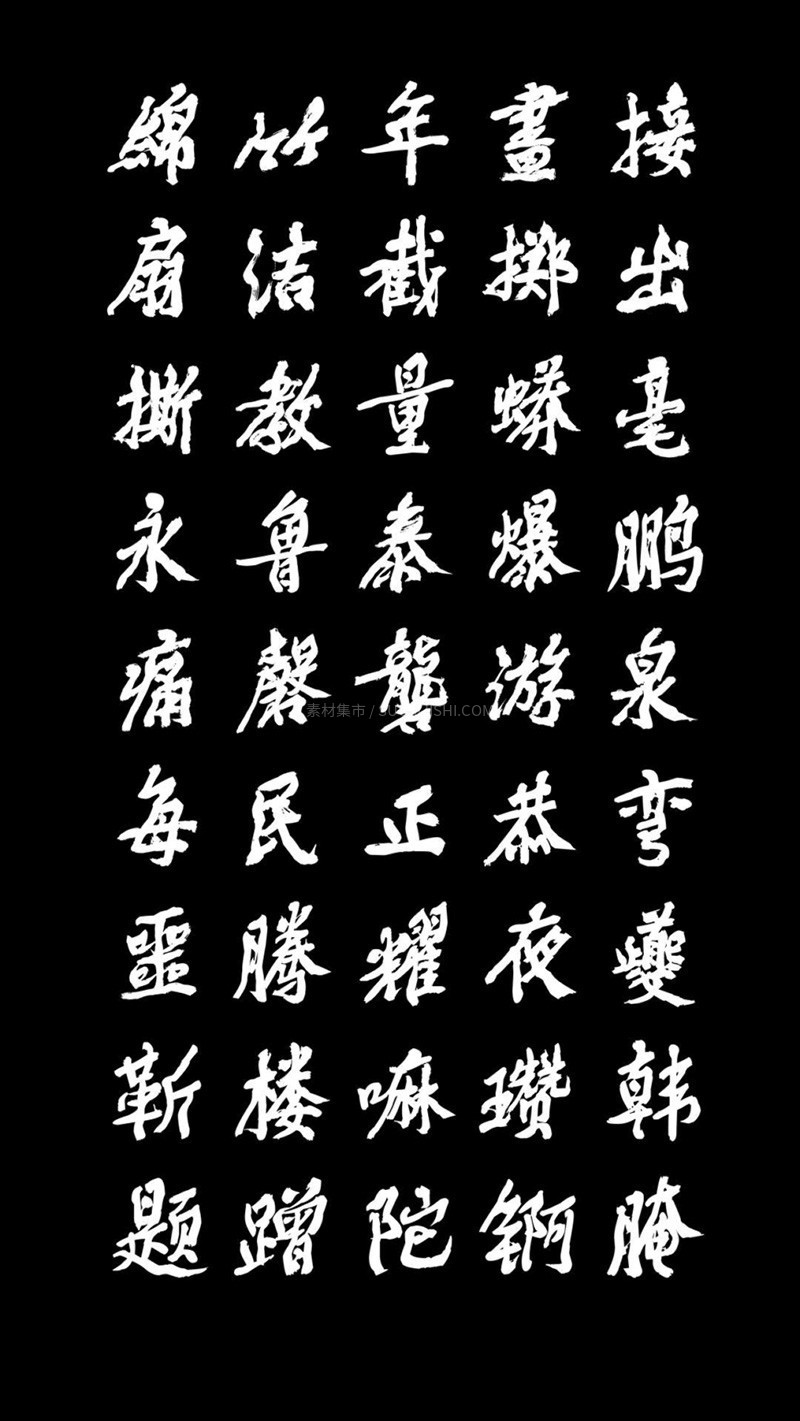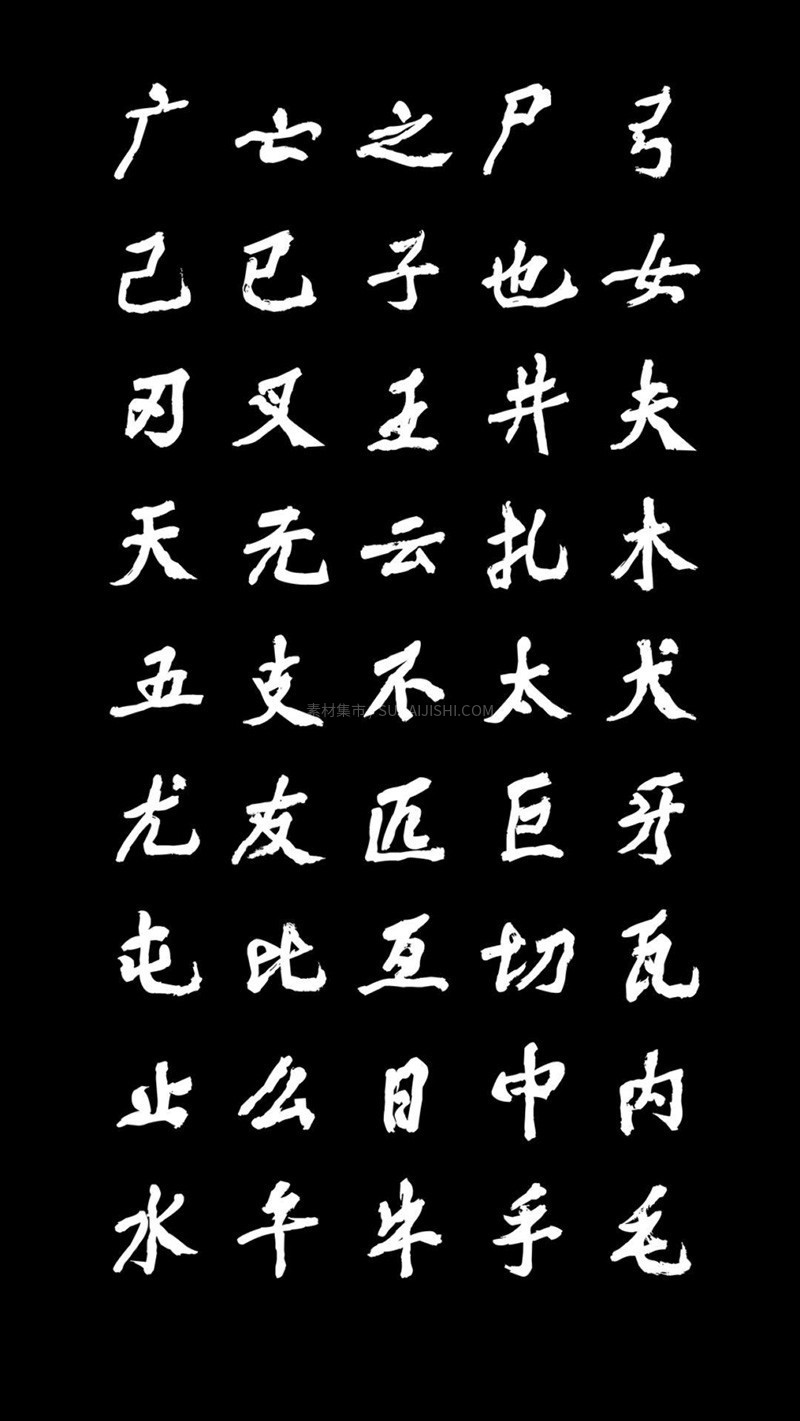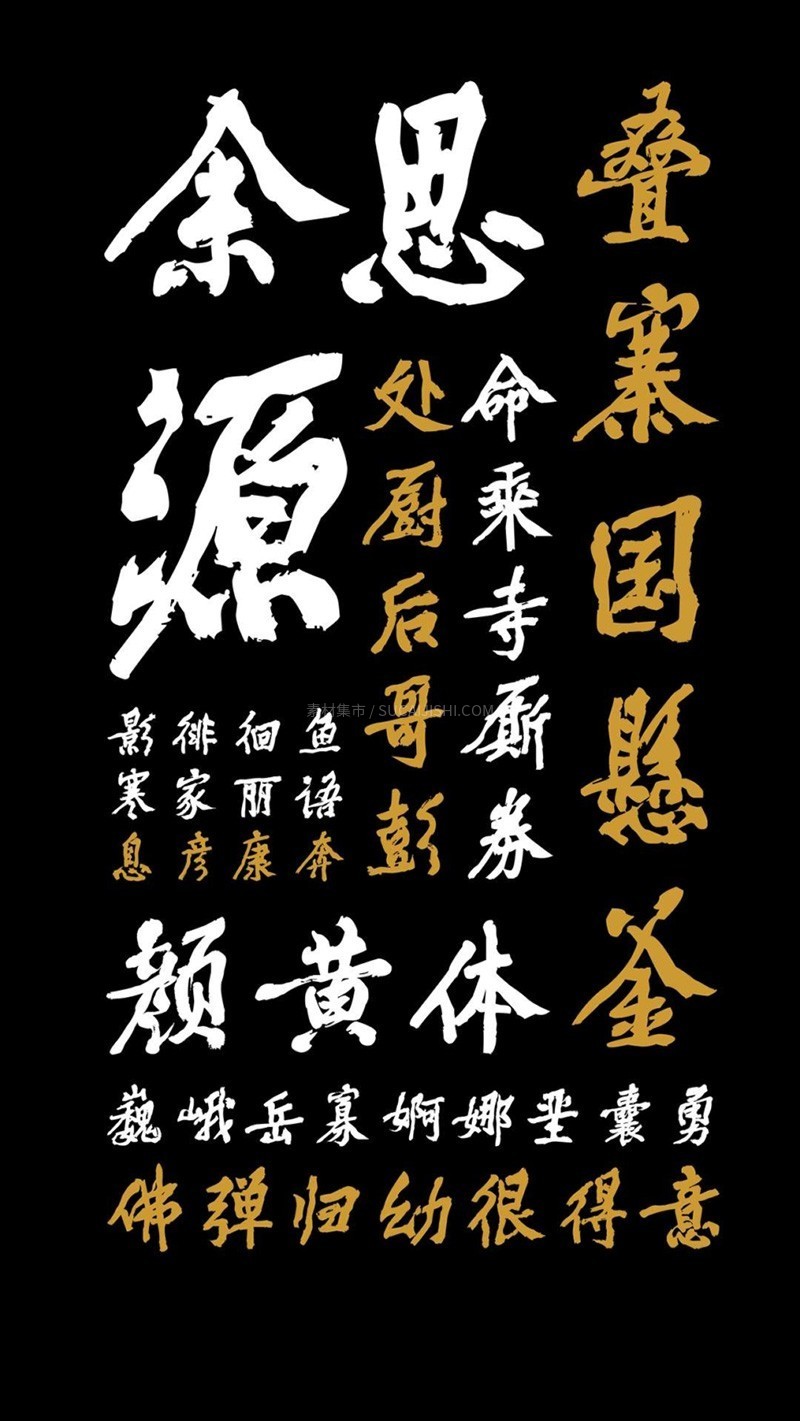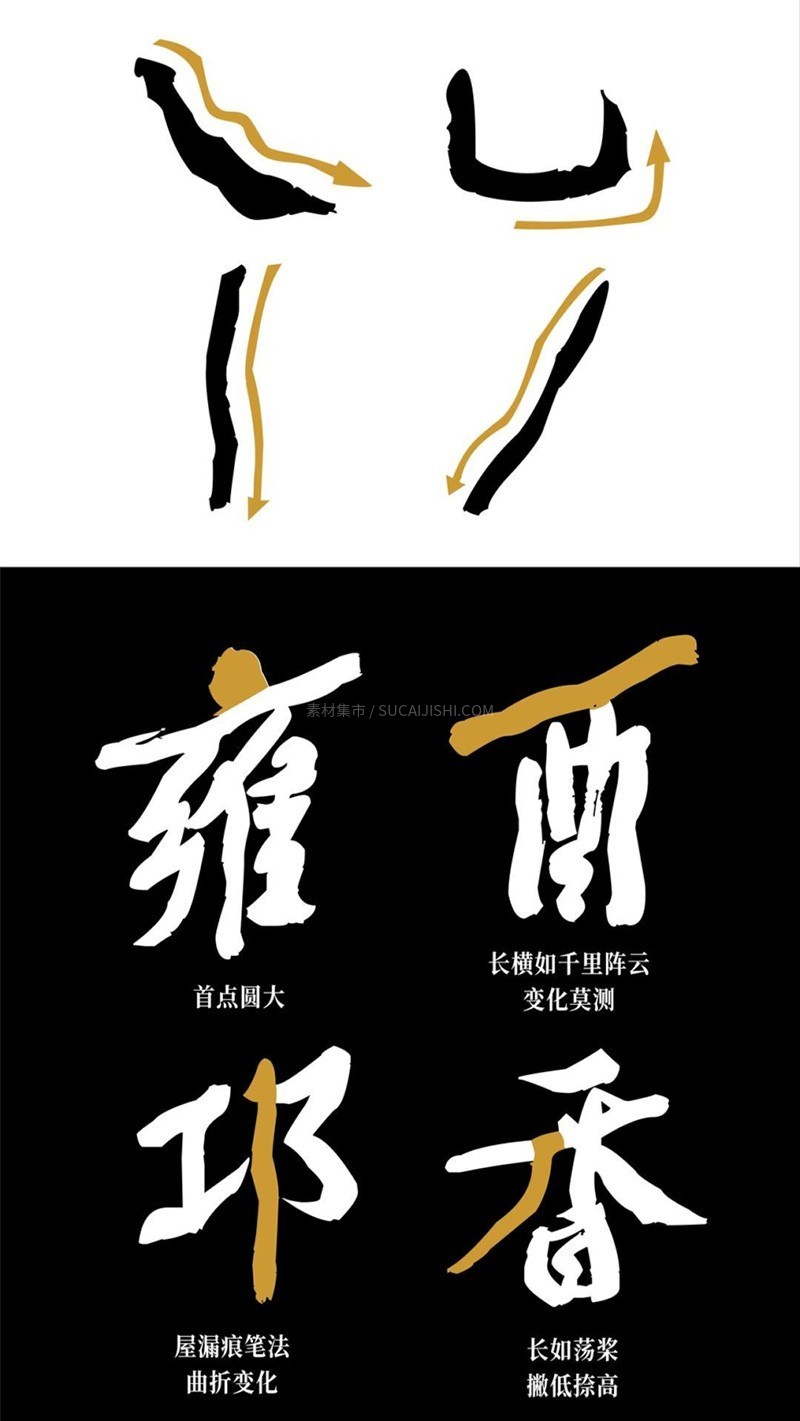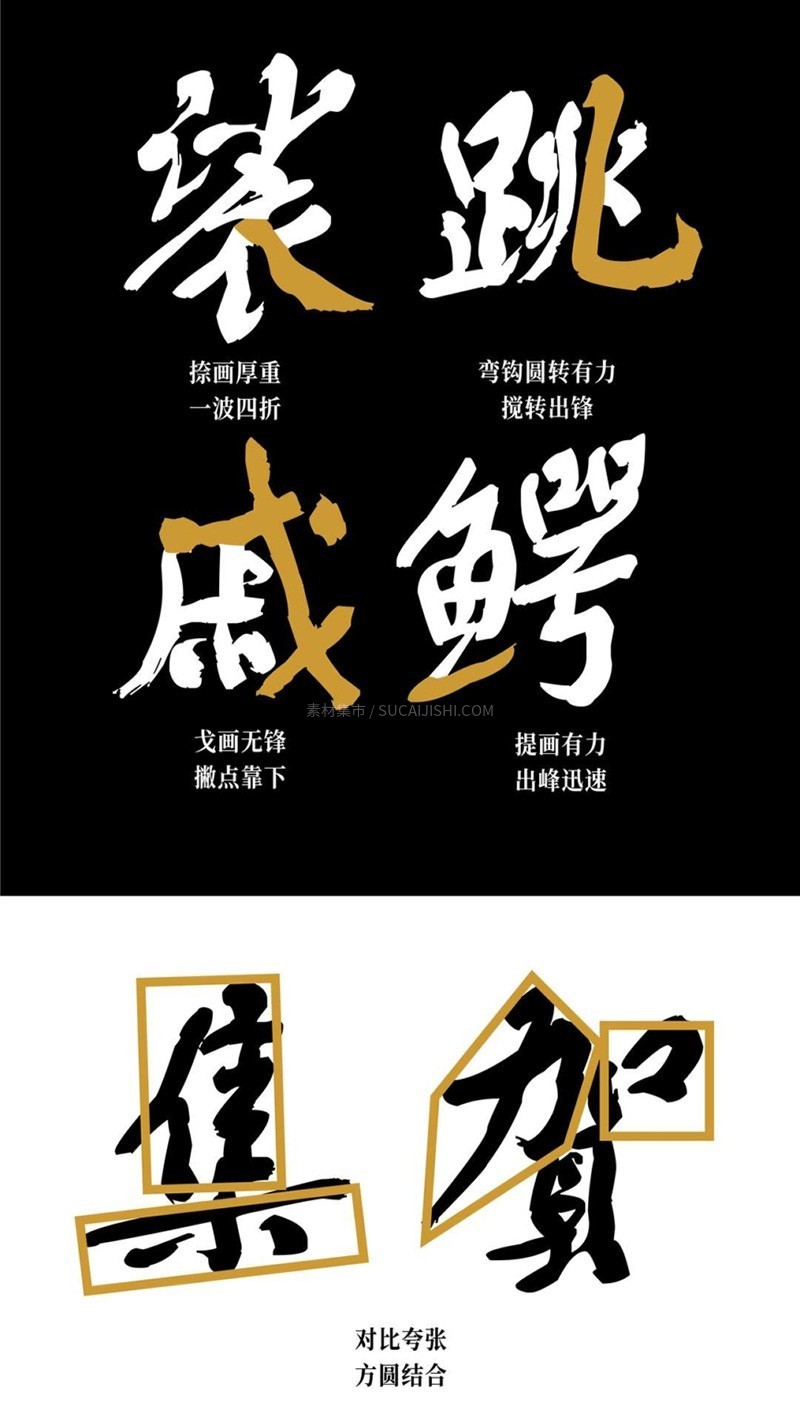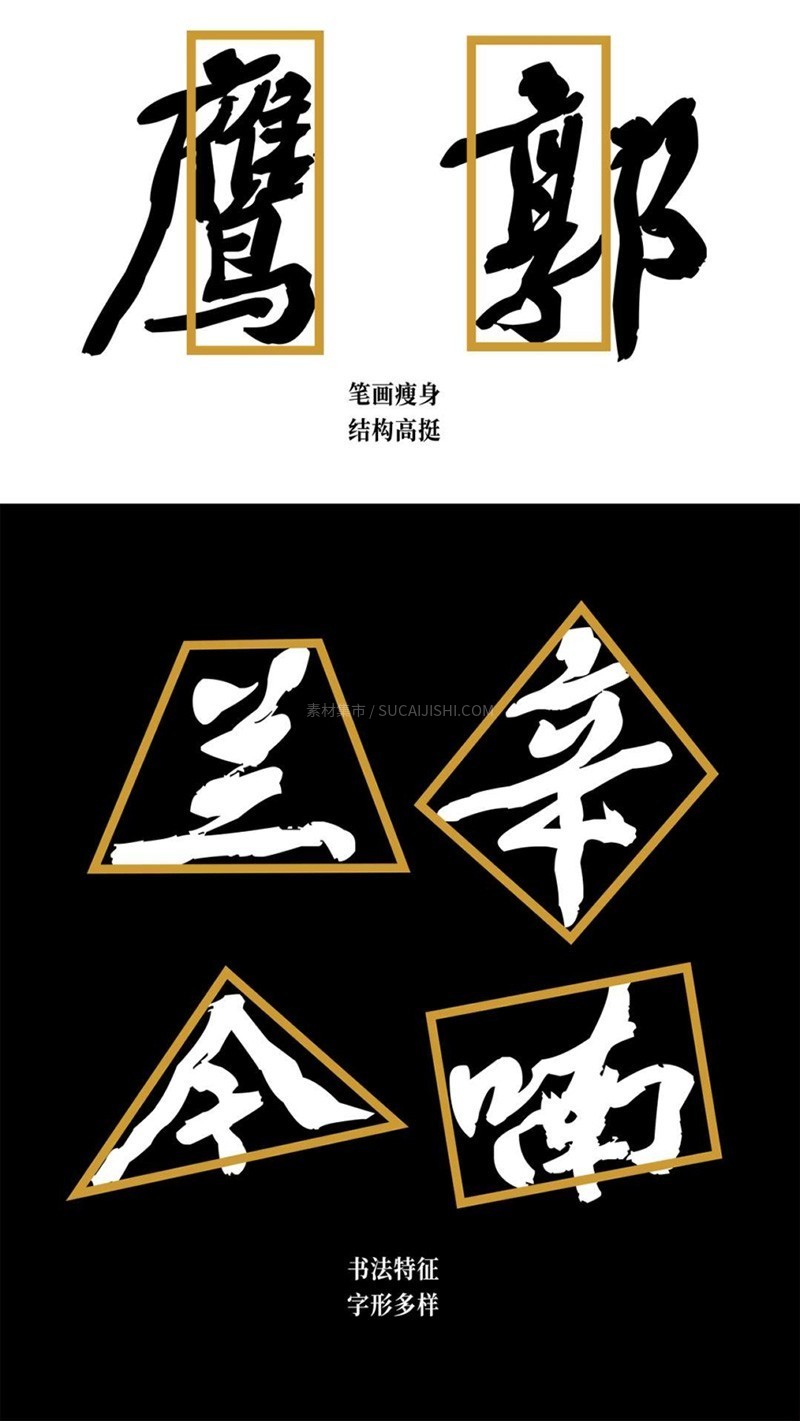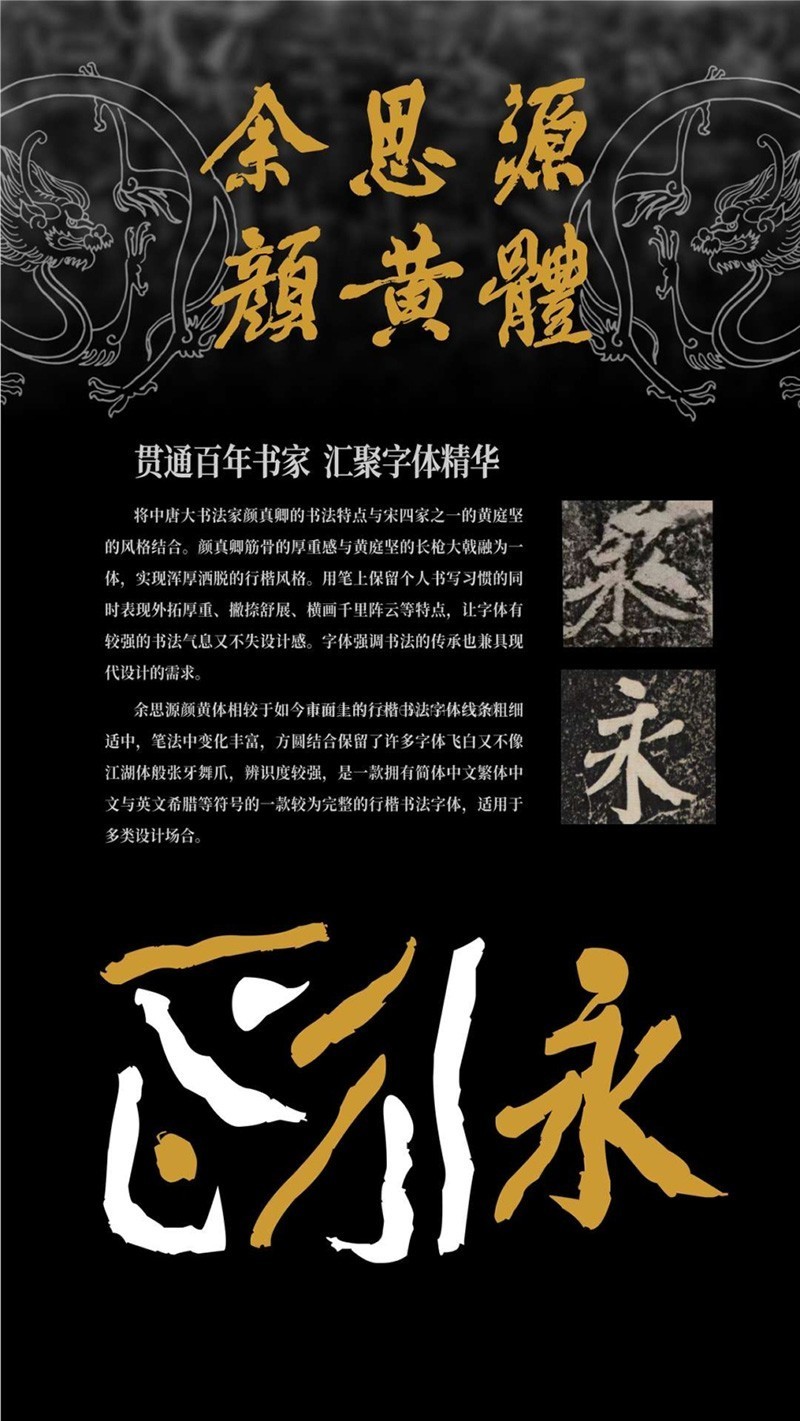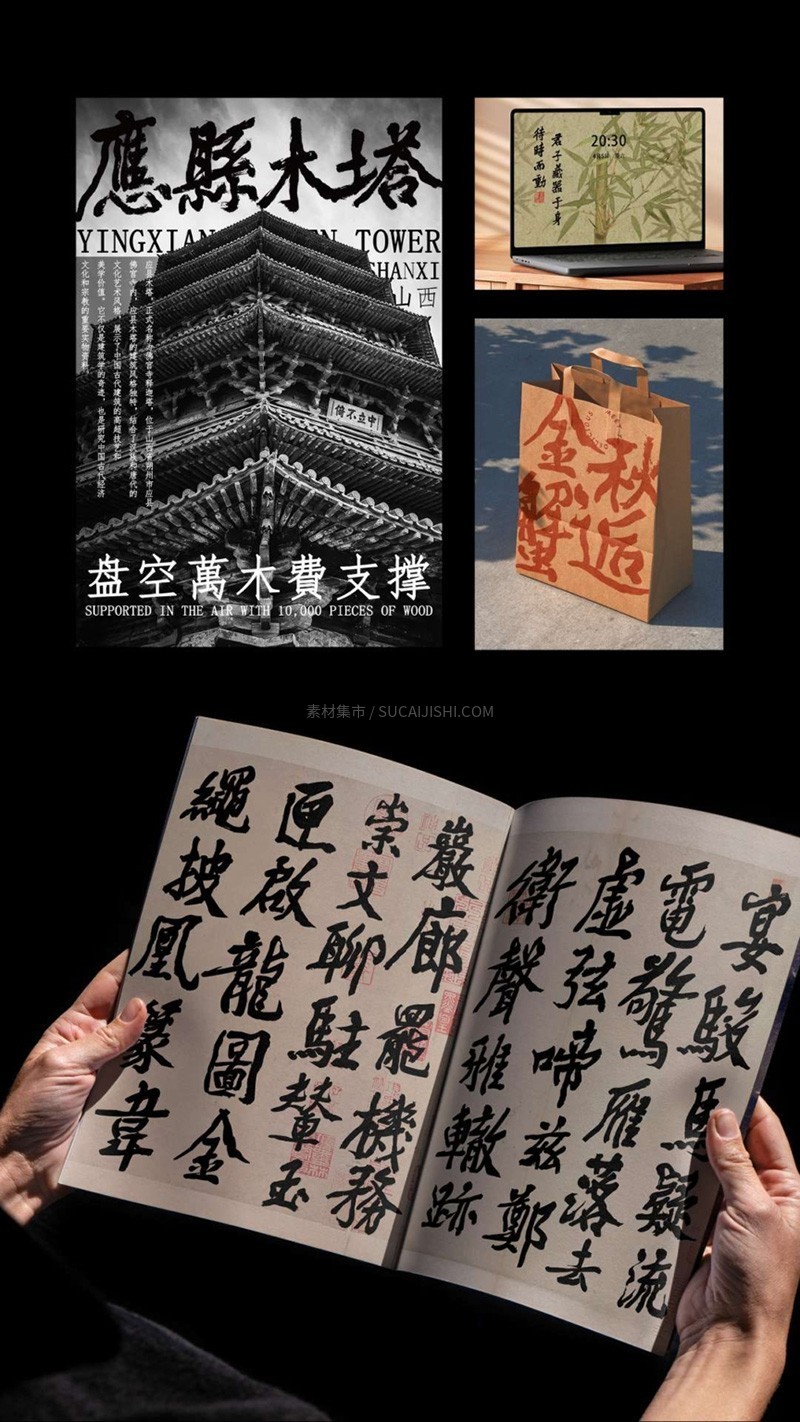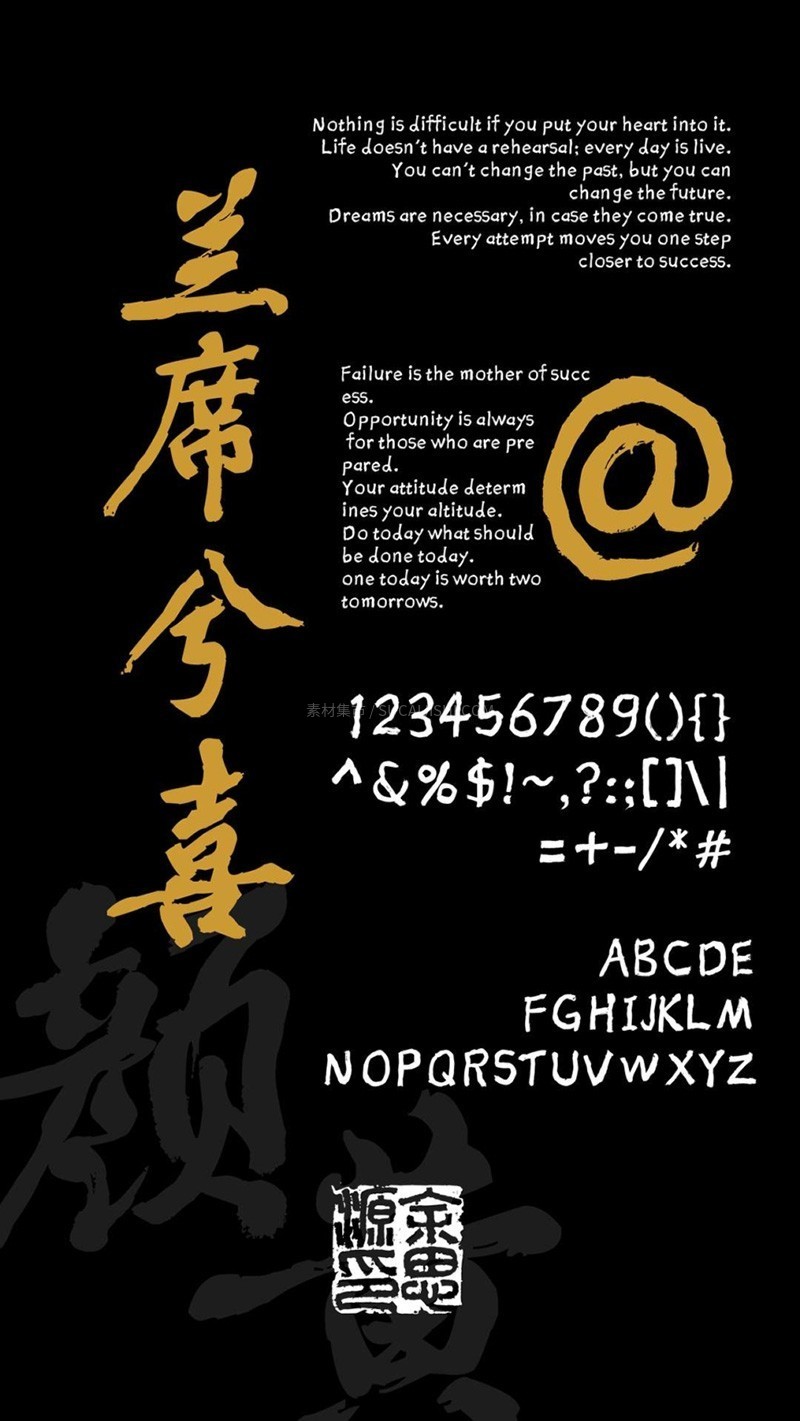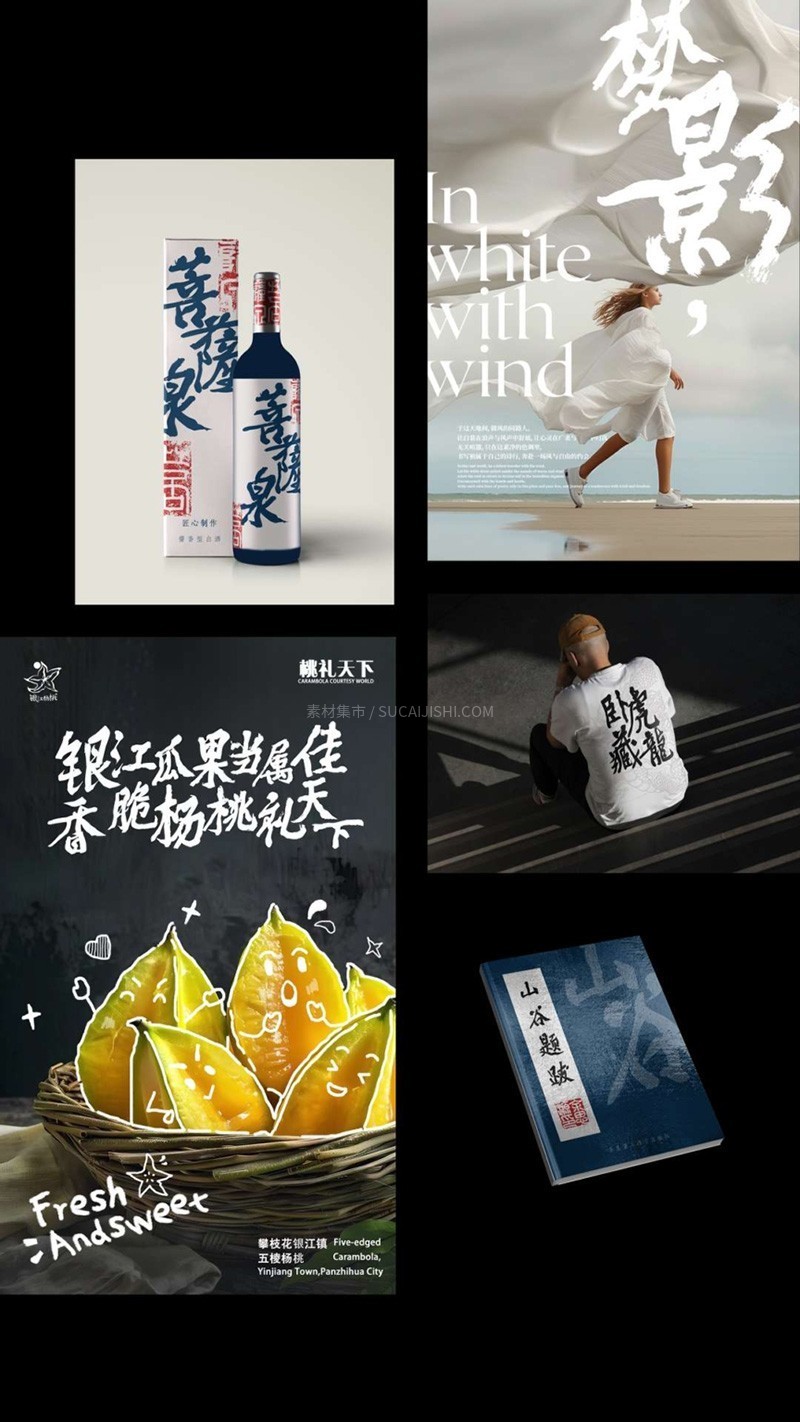
余思源颜黄体,免费可商用
余思源颜黄体是一款可免费商用的行楷字体,它将中唐大书法家颜真卿筋骨的厚重感与宋四家之一黄庭坚的长枪大戟之势融为一体,实现了浑厚酒脱的风格。用笔上保留了书写习惯,同时表现出外拓厚重、撇捺舒展、横画千里阵云等经典笔法特点。这款字体拥有较强的书法气息,又不失现代设计感,完美兼具书法的传承与现代设计的需求。相较于市面上的行楷字体,余思源颜黄体线条粗细适中,笔法变化丰富,方圆结合,保留了许多飞白,却不像江湖体般张牙舞爪,辨识度极强。作为一款拥有简体中文、繁体中文、英文、希腊字母等符号的较为完整的字体,它适用于多类设计场合,是您提升设计品质的理想之选。且完全免费用于商业项目!